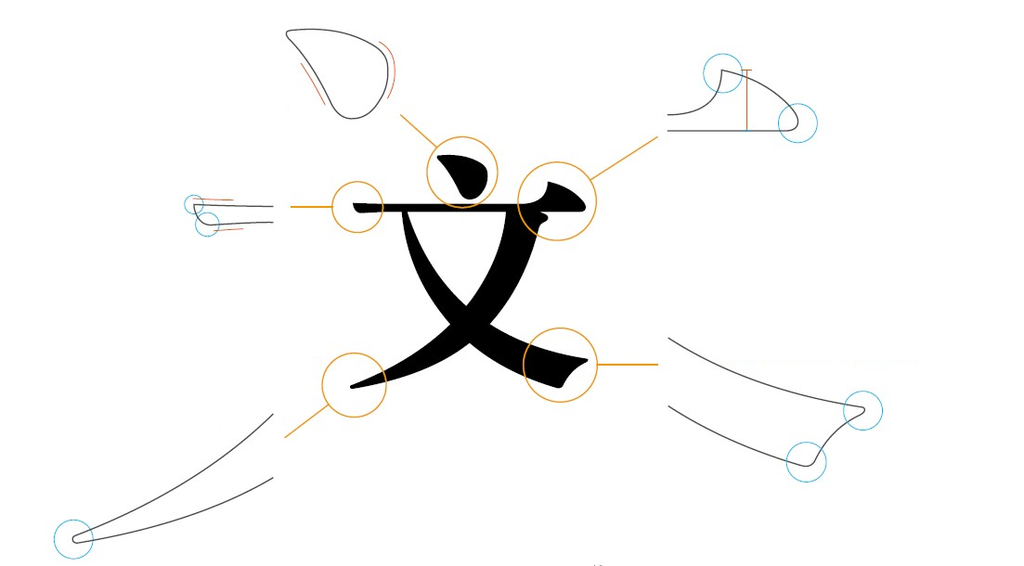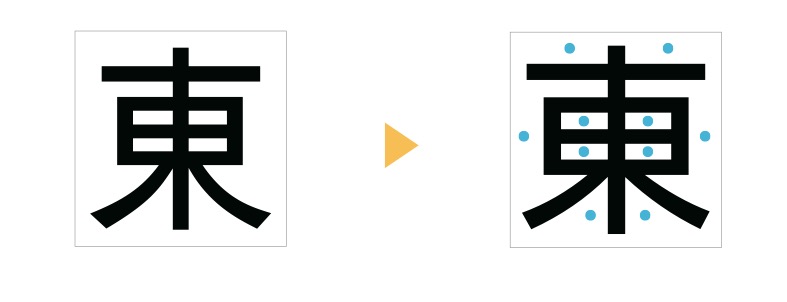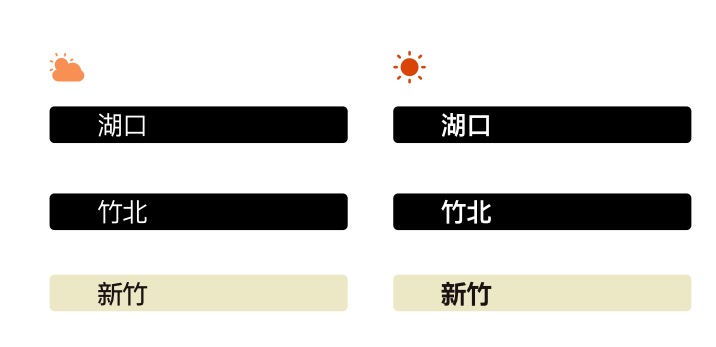
二十五年研磨台灣字體之美—專訪文鼎科技
各位讀者還記得,去年在網路與設計圈紅極一時的 「金萱」募資案 嗎?的確,金萱讓越來越多的台灣人重新注視與思考我們每天所使用的「字」。不過,能足以代表台灣本土的字型絕非只有「金萱」一者。受到聶永真的工作室與蔡英文設計團隊青睞,並榮獲 2013《Good Design Award》BEST 100 大獎的文鼎晶熙黑體,就百分百完全來自台灣。INSIDE 本次專訪文鼎公司,為讀者細數晶熙黑體與文鼎至今 25 年的故事。
從台灣字體的來源談起
一切得從漢字的印刷體演變與傳播史開始談起。我們現在一般所稱的「宋體」的確開端於宋朝,然而,它是從明朝中葉開始為了因應專業大量印刷,將仿宋刻版書楷體轉化為橫細直粗、四角整齊,專為印刷所發展出的字體,並在明末發展逐至成熟,這也讓日本事實上將宋體稱為「明體」(就是新細明體的明體)。而到了清末日本步入現代化道路時,出現對漢字印刷大量需求後為日人本木昌造從中國上海的美華書館導入包括鍍字法、字模等完整技術。因此中國與日本同時保存並發展自己的漢字設計與印刷體系至今。
然而就跟過去是部「殖民史」一樣,文鼎董事長楊淑慧為我們解釋過去台灣一直沒有源自本土的字型設計,而在殖民歷史脈絡下,字體設計與其技術皆傳承自日本,例如照相排版、鉛字模等都是學自日本的技術;至今也因日本現代化較早,在技術、機器設備的發展都較為先進,台灣字型的「日本血統」一直都相當濃厚。
直到數位排板崛起,進入電腦時代有了中文化電腦需求,台灣才真正開始發展自己的字型。換句話說,與日本與中國不同,台灣本土字型從一開始就是 80 年代 的「資訊時代」產物了。無論從傳統的出版、印刷,到電視螢幕或甚至是電腦裡所顯示的每個字元,資訊時代從頭徹尾改變了人們的用字需求。
但也正是晚至電腦時代才開始發跡的因素,台灣字型設計在初期確實缺乏自己的色彩,楊淑慧敘述當時環境:「由於剛開始台灣從事字體設計的人就是軟體工程師,雖然一方面沒有包袱,但也沒有文化傳承,這讓台灣初期的字體缺少了『底蘊』。」文鼎就是在這特殊歷史背景下,因應數位字體需求開始出現而生。他們察覺數位化即將徹底顛覆過去出版業,並體認台灣到確實缺少自己的字型而選擇「字型設計」作為立業的契機。
「這一行是軟體與設計的結合,一方面需要編寫造字系統,並適用在各種裝置與軟體上;另一方面設計端必須同時考量不同的環境、載體,依照實際需求與美學因素設計。數位字型設計本身就是一種工業藝術,字體本身要被工業化大量採用,但同時必須富含設計能量 。」楊淑慧如此形容數位字體設計這一行。
台灣失落的環節
不過,台灣有著雖然因半導體蓬勃迅速發展,卻同時缺乏版權概念,被世界稱為「海盜王國」的那個年代。這讓字型設計這行在台灣一路以來並不好走,其中最關鍵的一刻就在於 Windows 3.1 中文版發表後,對中文世界而言從此樹立「字型」定義成公開的資源,以檔案與軟體的形式存在於數位世界,這也讓字型設計在當時台灣被定義成「純軟體廠商」。
原先在 1985-2000 年間,台灣前後總共出現了十幾家研發數位字型相關業者,可是在當時台灣社會盜版風氣盛行也缺乏執法手段的環境下,最後只剩下有能力擴展國外市場的個體得以存活。楊淑慧語重心長的說:「這不光是字型設計業者的問題,2000 年前整體在國民普遍愛用盜版的狀況下,軟體業根本很難練兵啊!這也是台灣科技業先前缺乏內容,只能往硬體製造端發展的主因之一。」
這也是為什麼文鼎會在 2000 年後轉入日本的主要原因。原先在 2000 年以前,文鼎還有相紙輸 (RIP) 的小型市場,一套字型尚有幾千台幣的收入,但也發覺這並非長久賴以為生的方向。到了日本後,無論是 MP3 Player 、音響、印表機、冰箱電鍋或是晚近的車用螢幕大大小小電子產品,甚至到工業使用的人機介面都有用字需求,文鼎就是以「嵌入式」服務,也就是提供這些電子裝置數位字型作為營收主力至今。
▲「嵌入式」字型需求埋藏各大大小小的電器裡
楊淑慧也坦白表示,文鼎是被日本市場給「磨」出來的。在整個亞洲中,日本業界非常追求排版印刷精緻度,這也他們的相關產業遠遠領先其他國家,連帶讓整個社會相當肯定設計與美學所帶來的價值。在這極高要求的環境下,文鼎自然而然必須在每個環節上符合日本所要求的品質。不僅如此,對文鼎而言 2000-2010 在日本十年之間是非常重要的發展期。由於日本電子商品本身就是全球導向,對字型需求也不只限於漢字或日文,文鼎也必須同時開發拉丁文字與其他語言所需要的字型,供給全球的消費者使用。換句話說,進入日本對文鼎而言也等同面對全球,進而發展世界級的開發能量。
晶熙黑體:二十年集大成
曾榮獲 2013 年《Good Design Award》BEST 100 大獎,並由名設計師聶永真的工作室精選,受蔡英文競選團隊青睞的「晶熙黑體」,則是文鼎在經歷進入日本的十年轉型期後,預見「行動閱讀」時代將來臨的心血結晶。特別是智慧型裝置興起後,人們的閱讀重心將瞬間從紙本閱讀轉移到數位閱讀上,這也直接讓字型設計發生新一代的需求。
文鼎設計所藍健維為我們說明了晶熙黑體的設計理念。從漢字的字體上來看,過去的標楷、明體都強調「中宮緊收」,讓字體盡量往內部收攏;不過進入印刷甚至後來的數位化時代以後,字體發展朝向圖像化、符號化的方向發展,數位用途所流行的「黑體」,就會將中宮放鬆,讓字體符合字面框滿足數位閱讀效果。而晶熙黑體中宮放鬆的程度相當飽滿,比起其他黑體字腔更外擴,讓字體在數位環境下具清晰且不易糊字的顯示效果;同時縮小漢字、符號字面大小的差距,有效降低視覺落差。
但真正讓晶熙黑體受到《Good Design Award》大獎青睞的主因,並不是只有將字腔外擴這麼簡單。嚴格說起來完整的「晶熙黑體」是一整套響應式的字體系統,其中蘊含文鼎自己開發的「Arphic Infinity Font」字體引擎,能將單獨一組的字型資料依照螢幕大小、解析度甚至到光線明亮等外在環境,自動調整字體粗細與大小。
同時整個「晶熙黑體、系列不是只有英歐文字母、繁簡中文或日文漢字這麼簡單,就連泰文、阿拉伯、印度文,甚至到波斯與希伯來文等全球一共 90 多國文字。一套字型家族有 粗細、長平、標題或內文等 48 套字體組合都含括在內;但更吃驚的是與一般 TrueType 字型比起來卻只有半套,壓縮比將近百分之一資料量。楊淑慧進一步表示, 未來 Google 的主設計概念「Material Design」,其賦予電子介面物理特性之概念,正好與晶熙黑體的響應式功能不謀而合 。
本土又時尚,讓晶熙黑成蔡英文設計團隊首選
談到晶熙黑體被蔡英文設計團隊選為競選主字體的故事,正好就是文鼎「重回台灣」歷程中的一段奇遇。文鼎在 2012 年進行組織調整,並開始將視角重新拉回台灣。初期文鼎在同時推廣晶熙黑體與雲端 iFontCloud 字型租賃服務時,就認為在台灣該主動找尋設計師洽談合作。
▲因兼具時尚與本土,晶熙黑深受蔡英文團隊青睞
「就連我們自己也嚇了一跳!」回憶起當初文鼎團隊第一時間接到聶永真工作室通知時,還不知道是要跟蔡英文設計團隊合作,只知道是要有比較時尚、雅緻的黑體需求。但過了幾天才知道,原來是蔡英文團隊拍板決定,要採用來自本土,具有在地化意義的字體。在這點上,晶熙黑確實是百分百從字體設計到程式開發,一切皆由文鼎自主在台研發所完成的字型 。同時,這也讓蔡英文團隊成為 iFontCloud 個人化雲端字庫服務的首位購買者。
賦予傳統新生命:書苑宋與方新書
為了再度回到台灣與中文市場,他們所做的努力不僅只有推行晶熙黑與 iFontCloud 這麼簡單。文鼎的新字體「書苑宋」才在去年 12 月獲得 2015 年金點設計「視覺傳達設計」以及「年度最佳設計」兩個獎項。然而,因應數位閱讀的黑體已成為時代主流,那麼為什麼文鼎會反其道而行,去推行應停留於書本印刷世代的「宋體」?
從功能上來看,宋體的高比差讓印刷後每個字都具有較強的辨識率,實質具有讓閱讀的認知率的功能。像我們看一般閱讀的文學、學術書籍或課本,會使用宋體印刷就是因為「唸起來比較快」。但換個地方,豎粗橫細的印刷宋體就相當不適合數位閱讀環境 (尤其橫筆視覺效果會隨解析度提高越來越弱,就好像斷掉一樣)。
文鼎因此採用響應式設計的獨門技術,讓書苑宋橫筆可以依照環境自動調整粗細,以符合電子閱讀的需求;同時加大字腔結構,放入更多楷體元素,試圖為過去機械感較重的宋體添增更多圓潤感與人文色彩。換言句話,文鼎正是想使用新的技術與設計,讓已有千年歷史的宋體重新活躍於數位閱讀時代。
同樣被文鼎寄以厚望的字體還有方新書。他們認為黑體視覺效果太重,並且已佔據大眾的眼球長達 15 年,方新書就是想「各取所長」,融合宋體清雅與黑體穩健所設計的新字體,讓字體有同樣的辨識效果,但又能減低視覺負擔。
眼尖的讀者不難發現,其實最近「文鼎」二字也越來越常出現在台灣人的面前。確實轟動一時的「金萱」募資案讓許多人開始重視字體的應用與發展,不過文鼎也從未在本土字體中缺席,甚至可以說是帶著豐沛的海外經驗再度踏回台灣。「擁有自己的字型設計,就等於取得自己文化的美感跟話語權 。」楊淑慧最後這一席話,道盡台灣字型設計者的理念與未來。